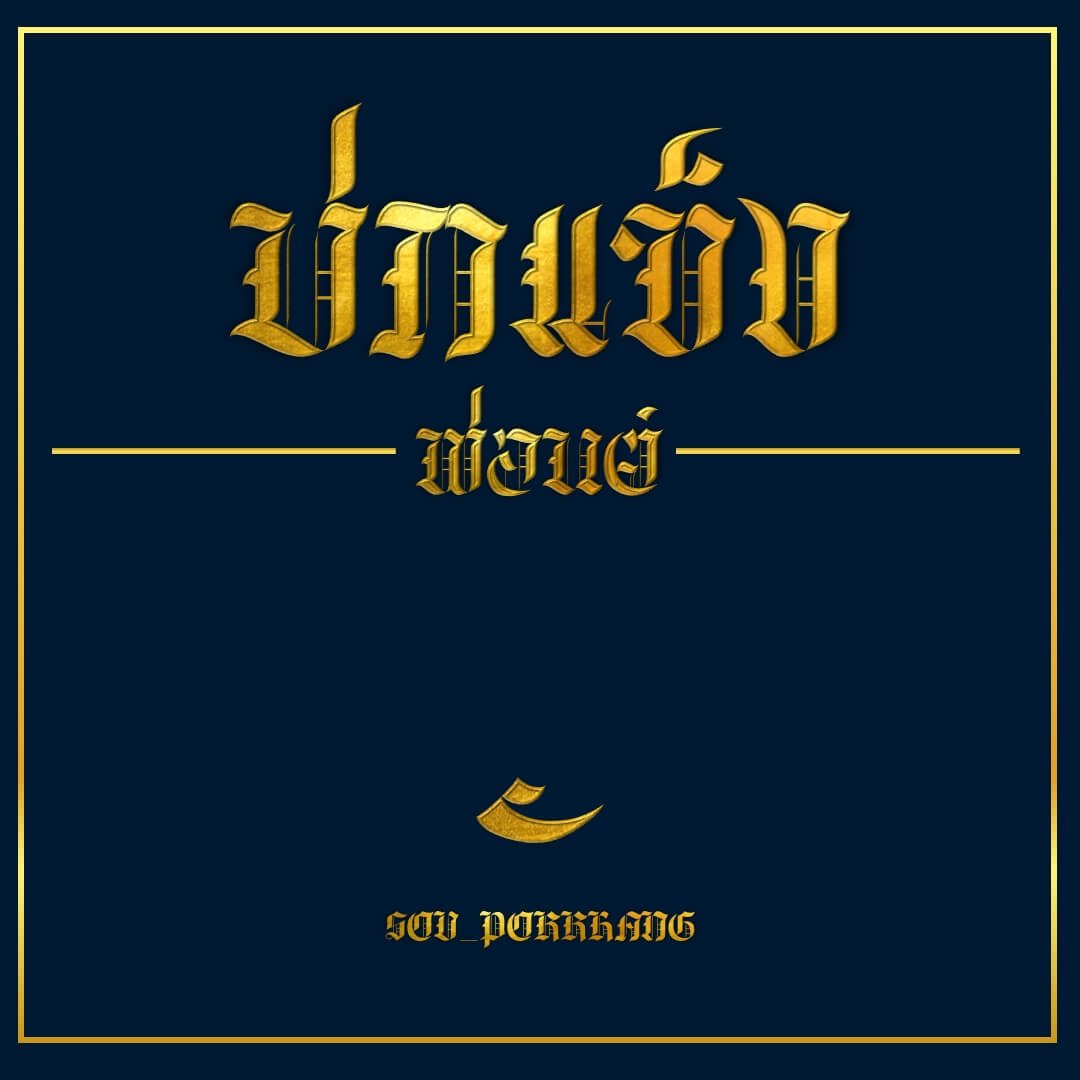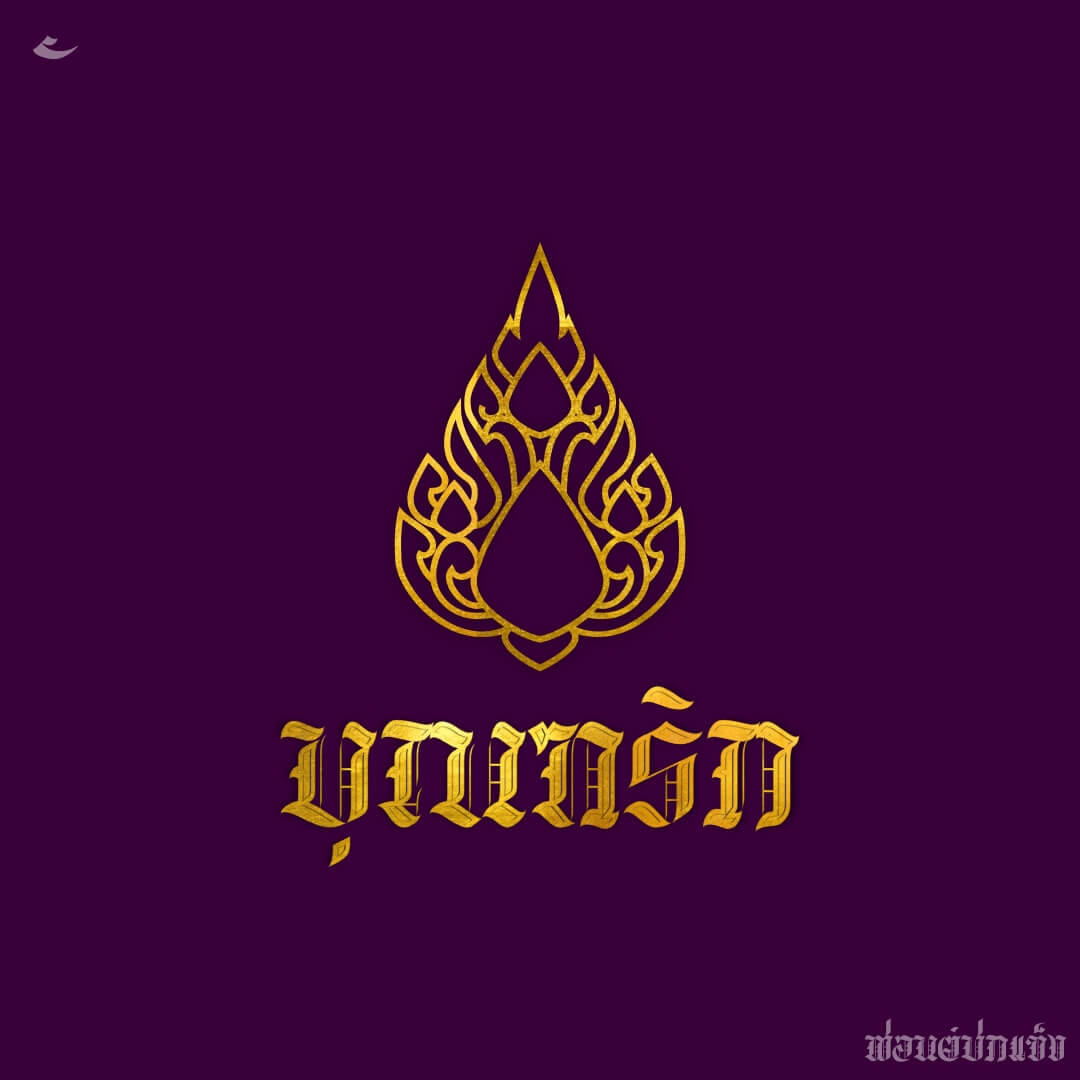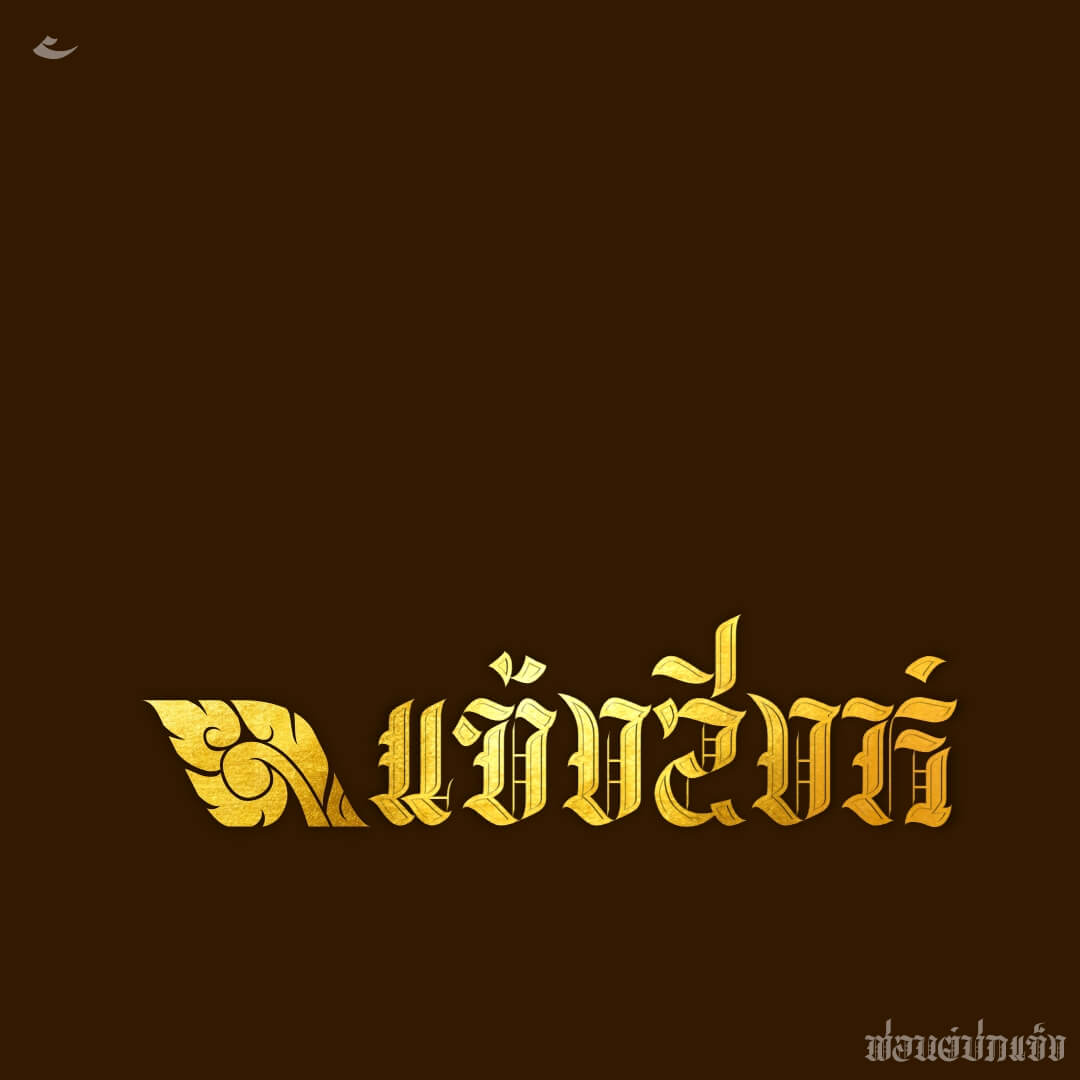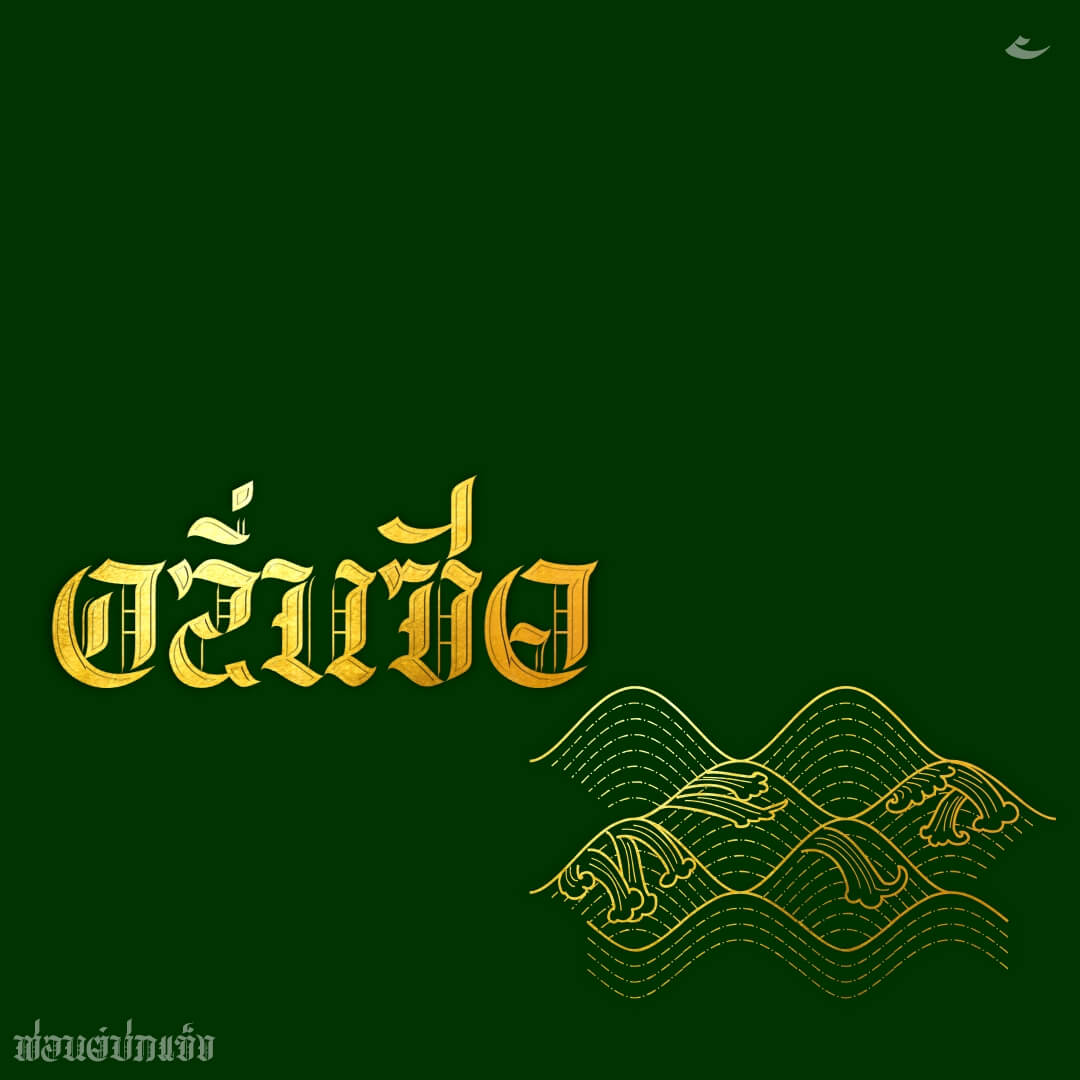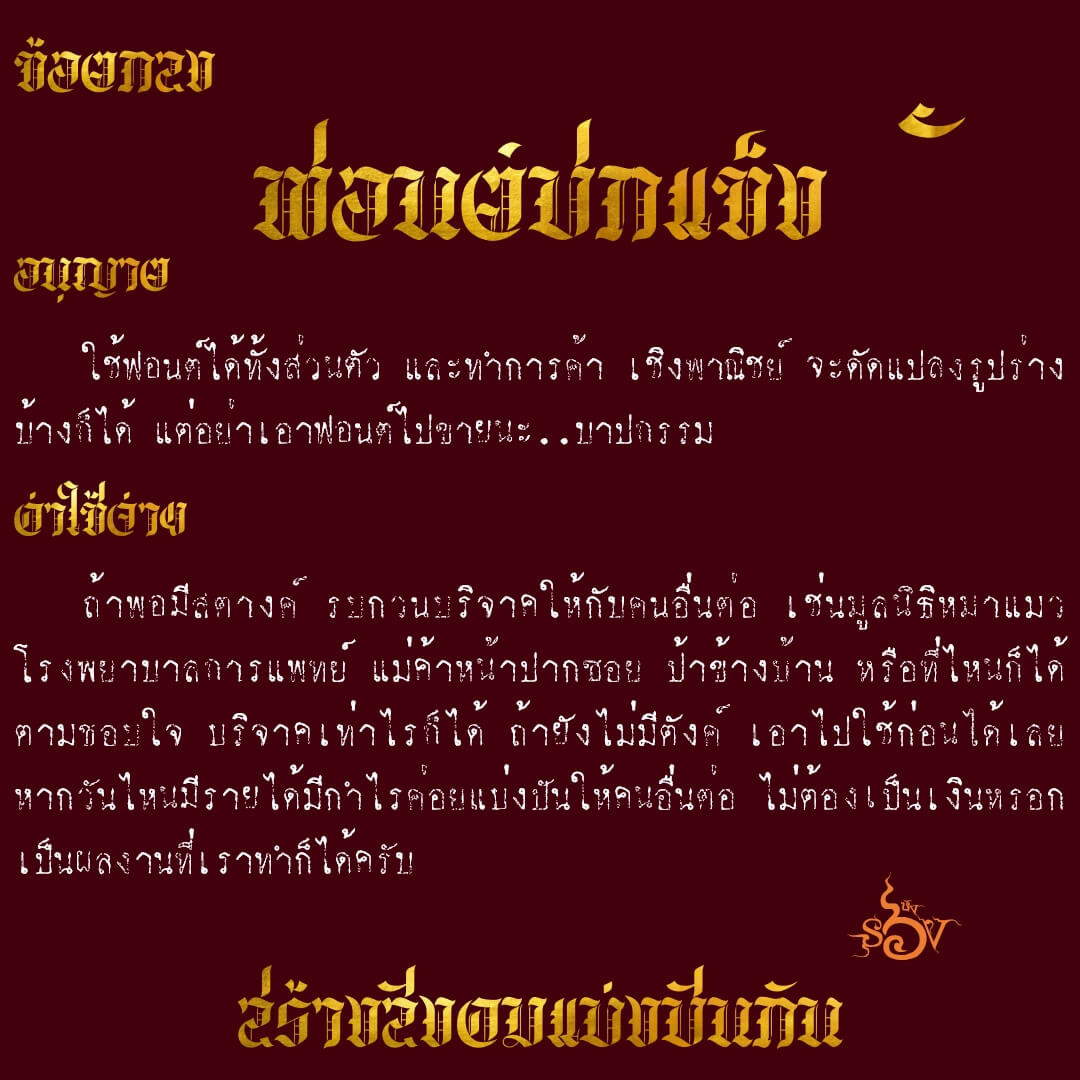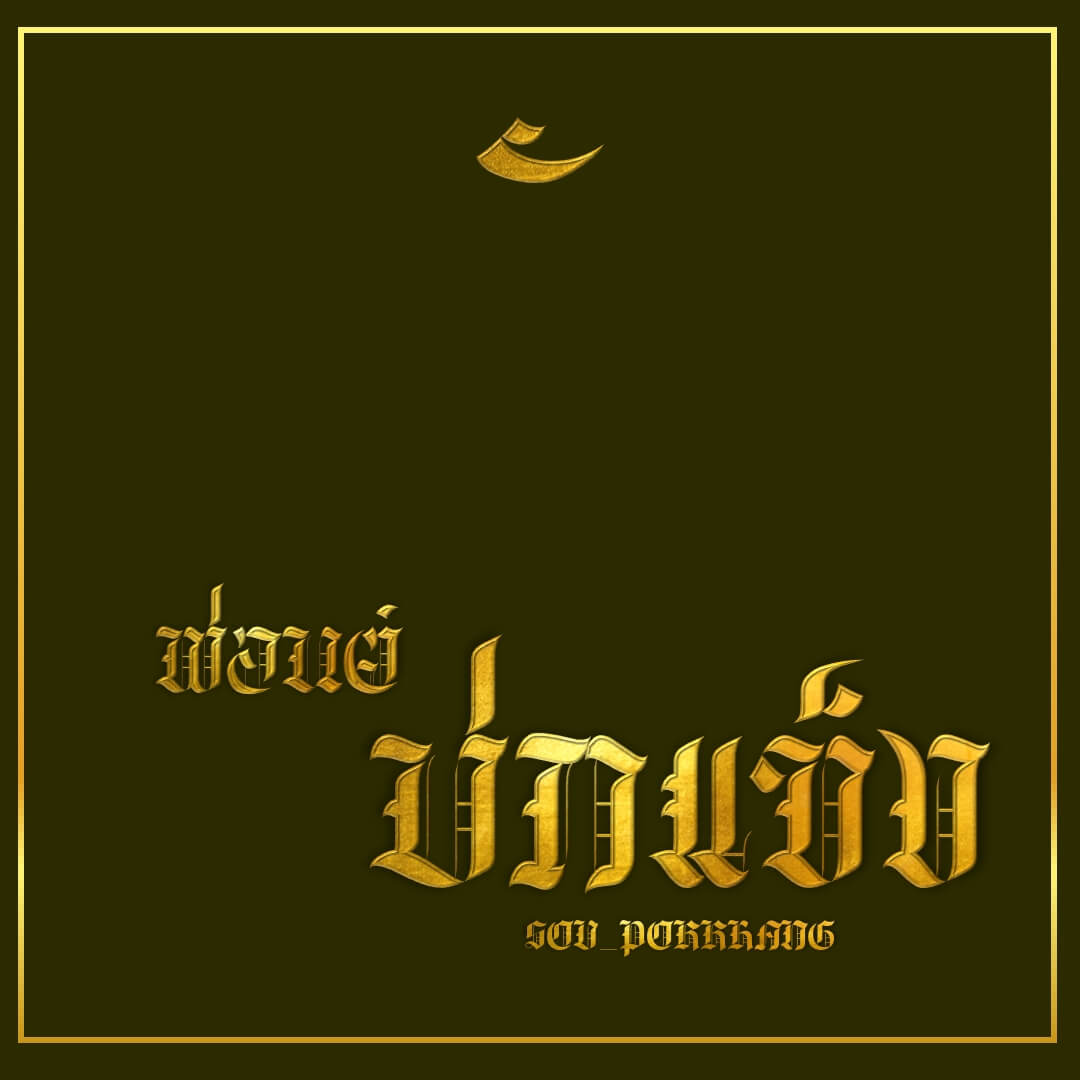
ฟอนต์ปกแข็ง – อักษรแนว gothic ที่ติดค้างไว้นานปี ทำเฉพาะ capital letters ตามแบบต้นฉบับที่เป็นปกหนังสือไทยสมัย 100 ปีก่อน เหมาะใช้เฉพาะคำสั้นๆ
เบื้องหลังการออกแบบ : ฟอนต์ ปกแข็ง
ปกแข็ง (SOV_PokKhang)